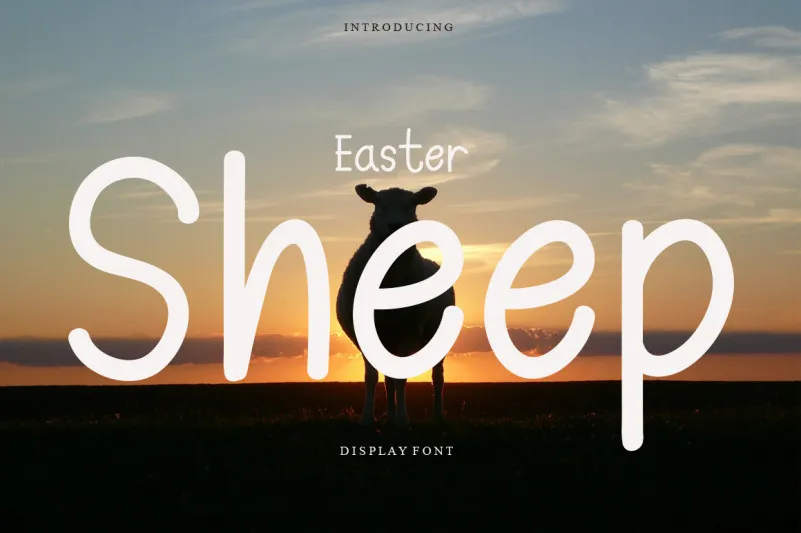
Easter Sheep Font – Download Grátis
Esta é uma fonte escrita a mão com um toque delicado e amigável. Suas características naturais e únicas a tornam perfeita para um leque ampliado de projetos gráficos. Experimente explorar as inúmeras variações que essa bela fonte tem a oferecer. Não importa qual projeto você estiver criando, ela se encaixa de forma única e harmoniosa. Aproveite!